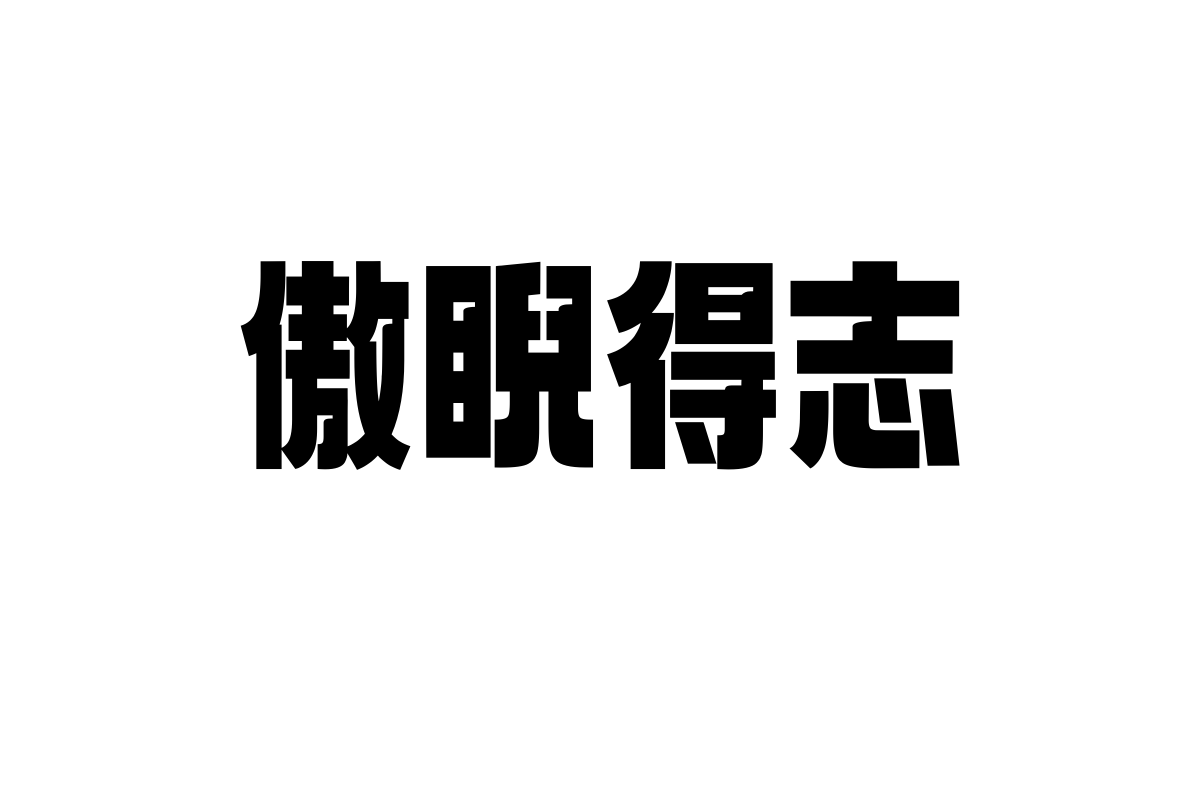
“上首亦方体”是一款具有独特设计的字体,它采用了方形的结构,给人一种简洁、大气的感觉。这种字体的特点是笔画简洁明了,线条流畅,易于阅读和理解。同时,它的字形也具有一定的艺术感,能够给人带来一种独特的视觉享受。
这款字体适用于各种需要强调文字的场合,如标题、广告、海报等。它能够很好地传达出设计者想要表达的主题和情感,使作品更具吸引力和感染力。
总的来说,“上首亦方体”是一款非常优秀的字体,它以其独特的设计和易读性,赢得了广大用户的喜爱和认可。